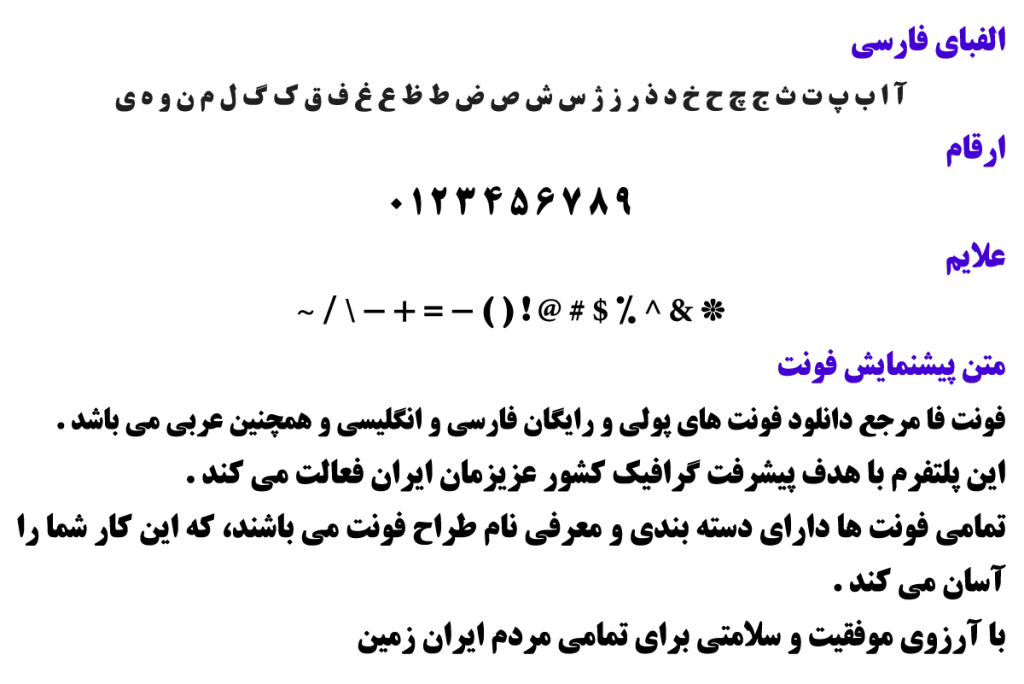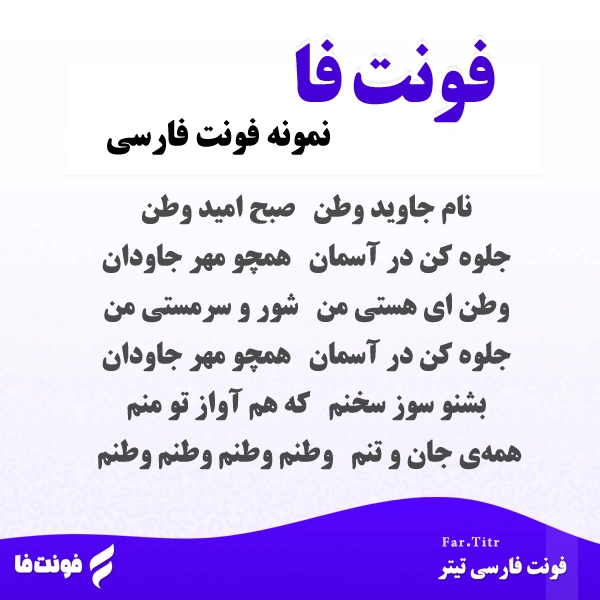
فونت فارسی تیتر – Far Titr
طراح فونت: ابوالفضل سيل سپور نوع فونت: فونت عنوان
توضیحات و معرفی فونت تیتر
فونت فارسی تیتر ( Far Titr ) از مجموعه فونت های آزاد می باشد، همچنین نوع فونت عنوان می باشد.
فونت فوق العاده زیبای معرفی شده توسط ابوالفضل سيل سپور در سال 1390 طراحی و ساخته شده است.
تیتر فونتی خوشگل است که تفاوتی زیادی با فونت تیتر و فونت تیتر پلاس و فونت نسخ تیتر دارد.
همچنین فونت Far Titr در یک وزن پر رنگ است.
- Far Titr Bold
شعر میهنی زیر با این تایپ فیس طراحی شده و نمایانگر زیبایی آن است.